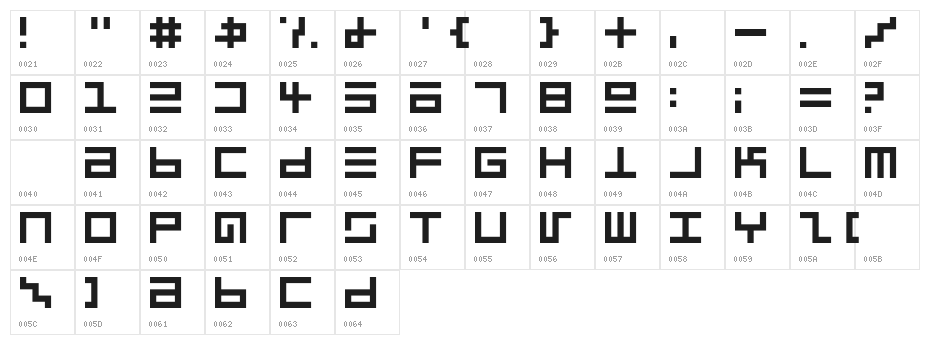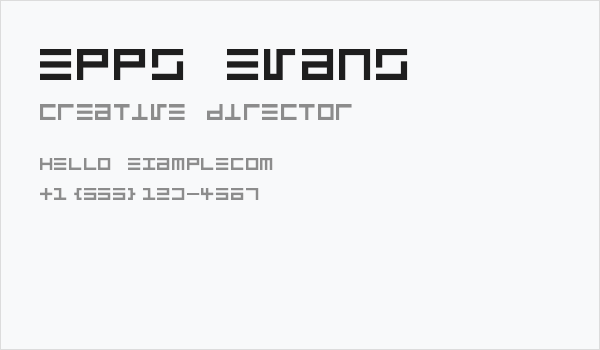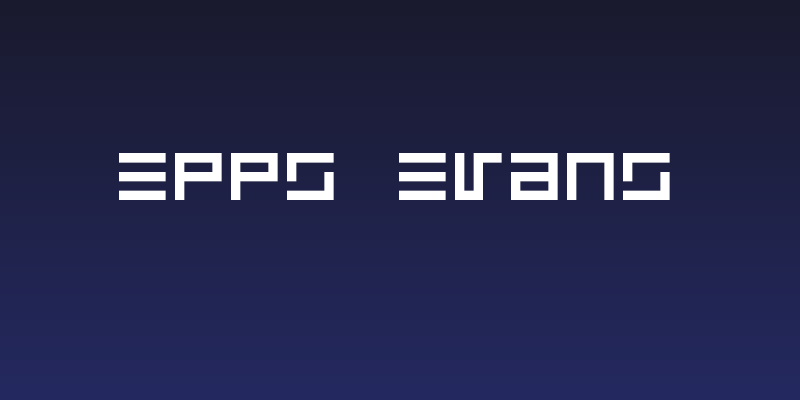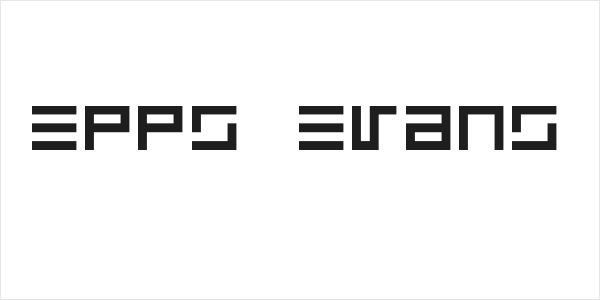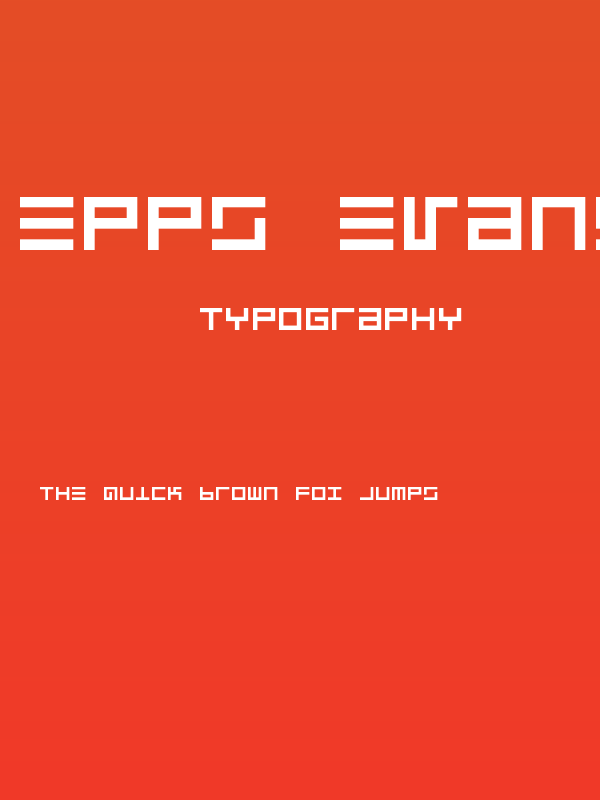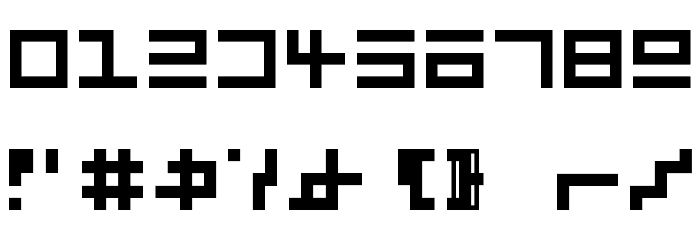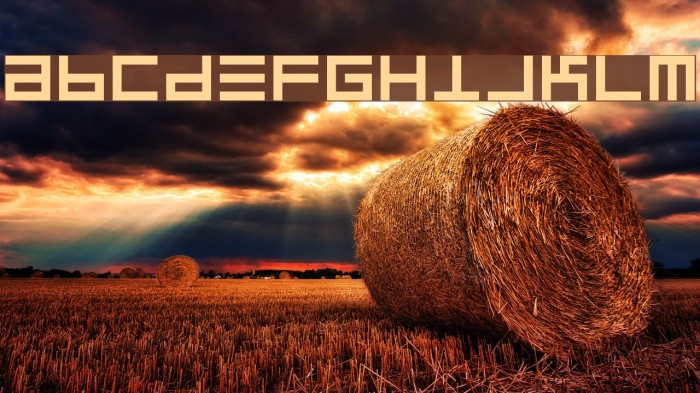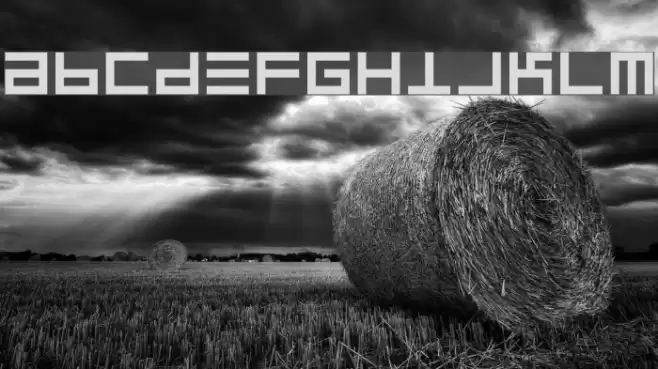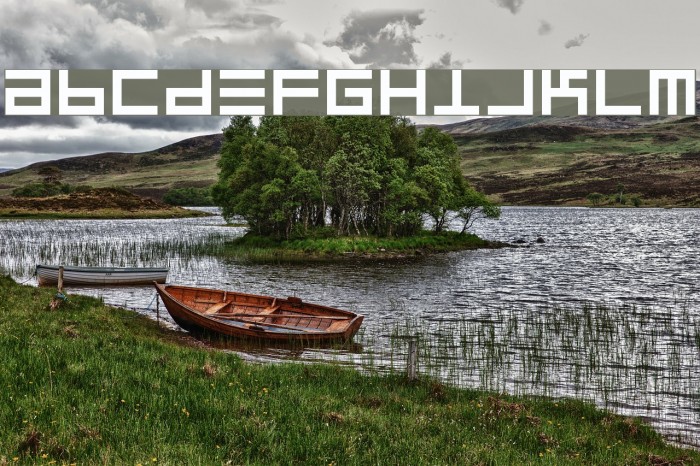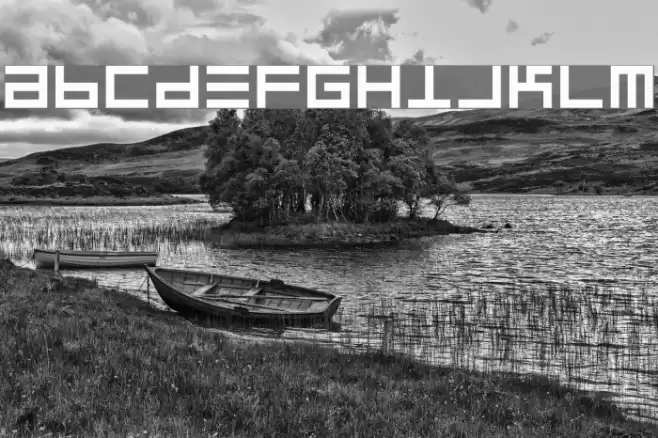
Epps Evans Font
| Proiecte propuse | Ideal for projects that require a modern, tech-inspired look, such as video game titles, tech company logos, or sci-fi movie posters. |